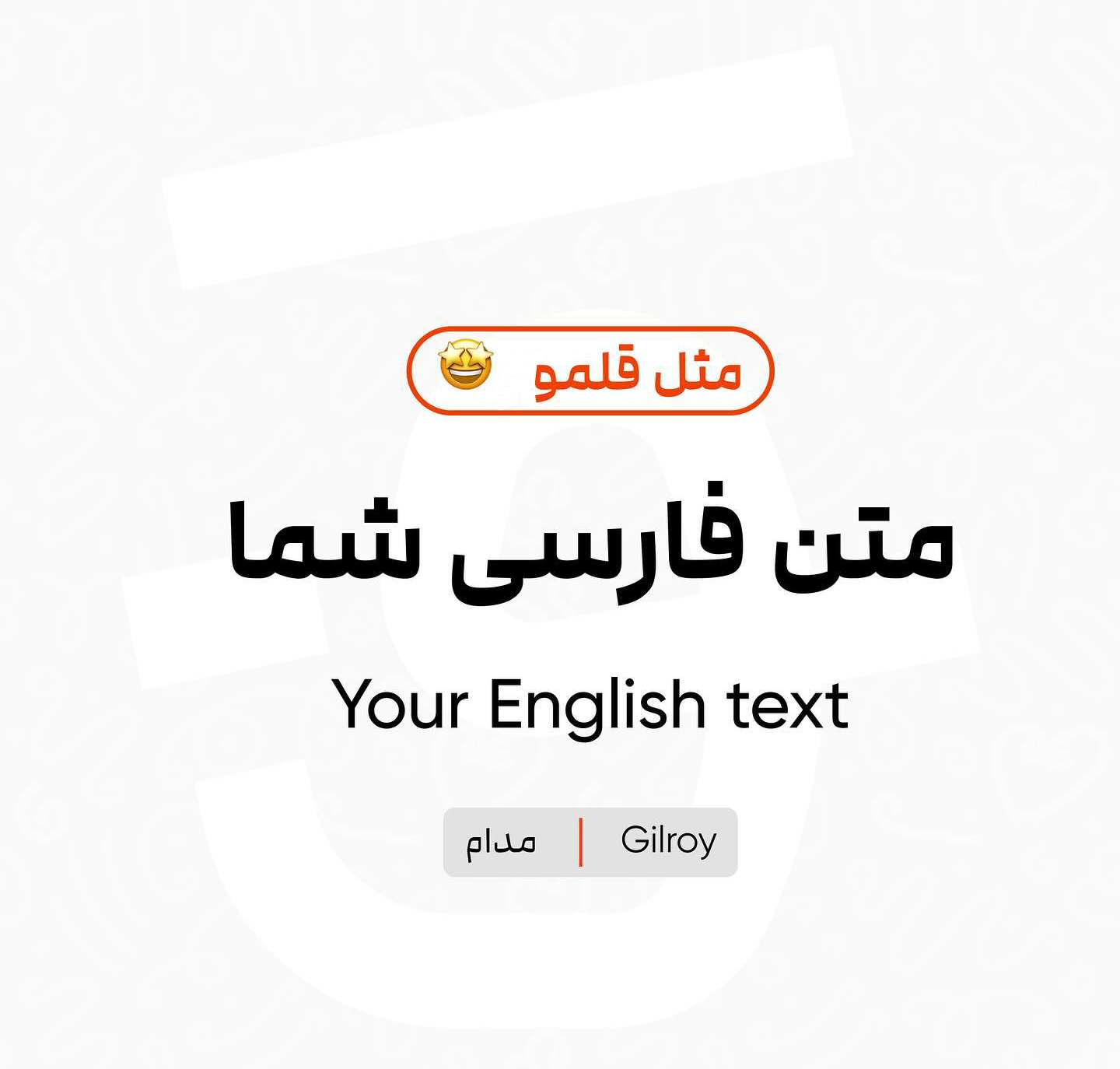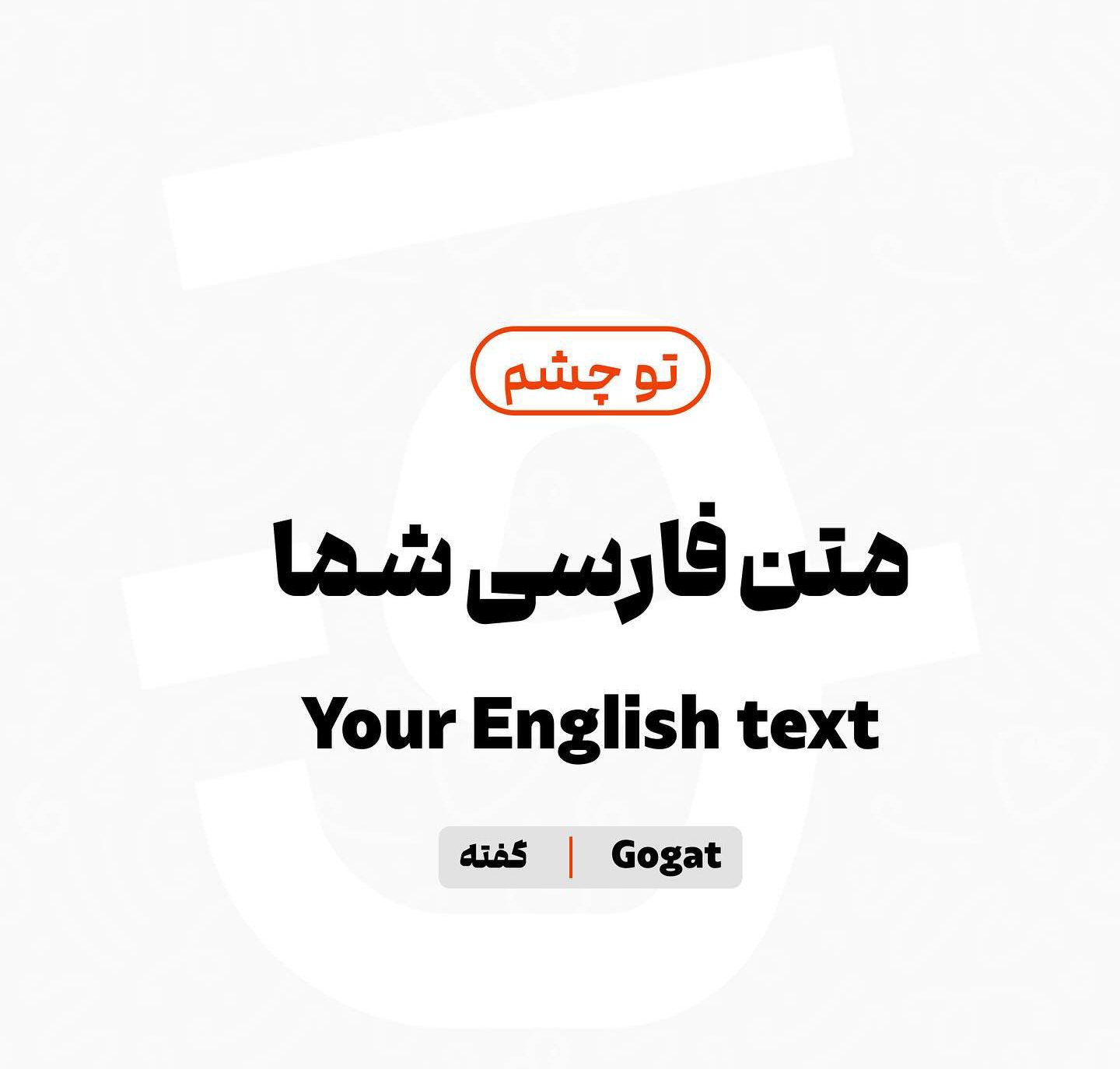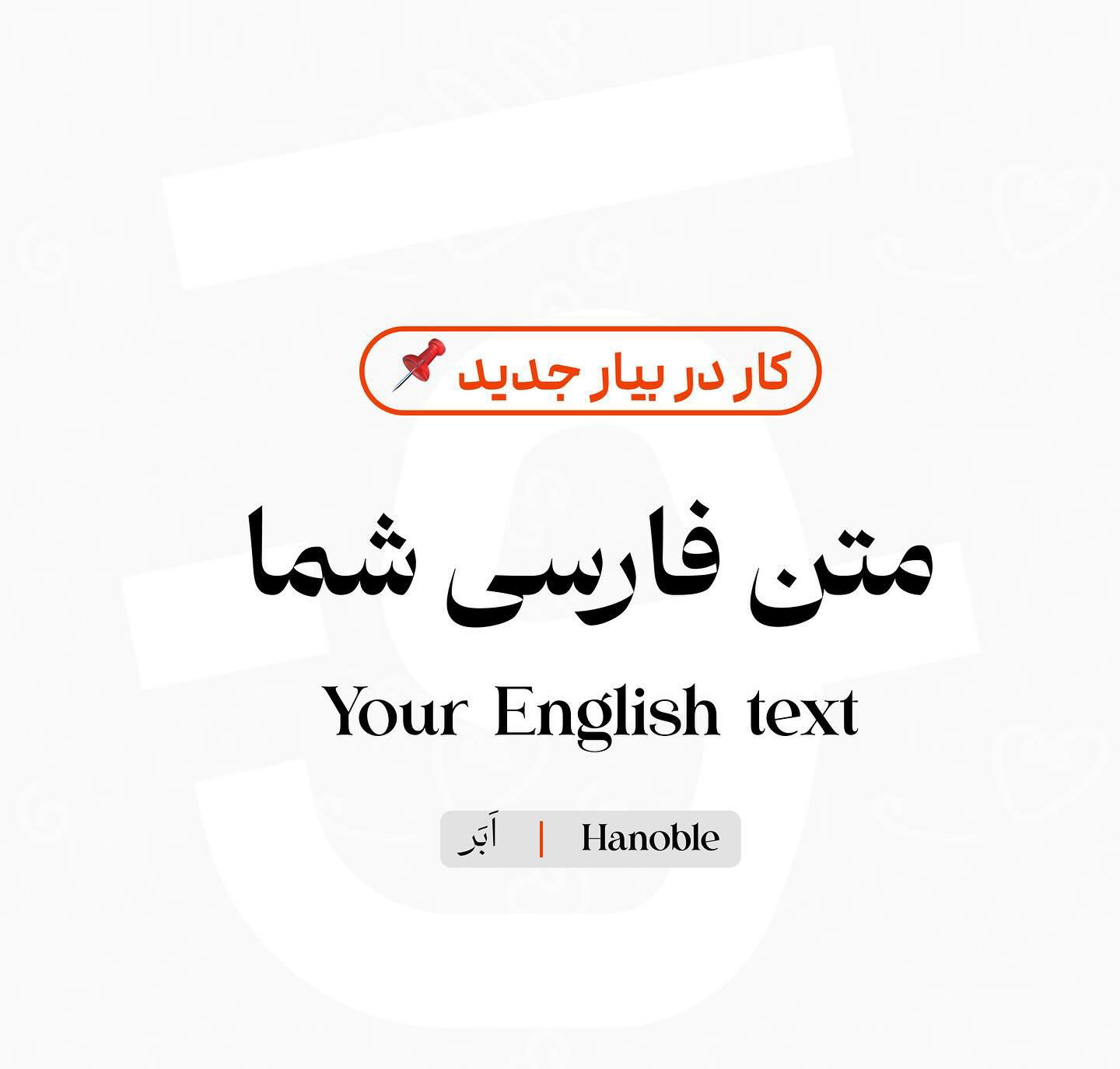
بهترین زوج فونت های فارسی و انگلیسی برای سایت
امروزه انتخاب فونت مناسب به یکی از اصول مهم طراحی سایت بدل شده است؛ چرا که مکملی بالقهوه برای شکلگیری و جانبخشی به صفحات وب است و به انطباق هرچه بهتر محتوا کمک میکند. در این میان انتخاب بهترین زوج فونت های فارسی و انگلیسی برای سایت هایی که ساختار چندزبانه دارند حائز اهمیت است.
ساختار حروف در دو زبان فارسی و انگلیسی با هم تفاوتهایی کلی دارد. به همین دلیل در طراحی فونت باید به شیوهای ضخامت، زوایای گردیها و چشمیها را در نظر گرفت که برای هر دو زبان مناسب باشد. در میان انبوه فونتهای فارسی امروز، طراحان به این نکته توجه ویژه دارند.
در ادامه این مقاله از سایت فونتچی، به بررسی چند فونت مختلف میپردازیم که ساختار طراحی حروف در آنها به شکل هماهنگ بوده و برای استفاده در سایت یا اپلیکیشن موبایل، میتواند ساختاری یکپارچه در اختیارتان قرار دهد. خصوصا برای سایتهای چند زبانه، که اهمیت خوانایی بین دو زبان بیشتر اهمیت پیدا میکند. علاوه بر آن به معرفی فونت انگلیسی مناسب برای هر یک خواهیم پرداخت که در صورت تمایل میتوانید از فونت جداگانه برای هر زبان استفاده کنید.
بهترین زوج فونت های فارسی و انگلیسی برای سایت
چند مسئله مهم در انتخاب فونت مناسب برای زبان انگلیسی و فارسی وجود دارد که عبارتند از:
- خوانایی حروف: فونت باید حروف را به طور واضح، خوانا و بهدور از اشکالات نمایش دهد. در هر دو زبان، حروف باید به خوبی تمایز داده شده و به اندازه کافی بزرگ و واضح باشند.
- تطابق شکل حروف: شکل حروف فارسی و انگلیسی در تمامی بخشها مثل زوایا، دندانهها، خطوط قائم و چشمیها با هم هماهنگ و یکپارچه باشد.
- رعایت فضای کافی بین حروف: حروف در زبان انگلیسی از هم جدا هستند؛ در حالی که زبان فارسی حروف به هم چسبیده کلمات را تشکیل میدهد. عدم رعایت فاصله حروف در زبان انگلیسی مشکلی است که گاها در برخی فونتها میبینیم.
- توازن بین کلاسیک و مدرن بودن: از آنجا که حروف کاملا متفاوت از هم بوده و کلمات از هم جداست، فونت باید توازن مناسبی بین ساختار کلاسیک و مدرن داشته باشد؛ به گونهای که با محتوای سایت هماهنگی داشته باشد.
- پشتیبانی از کاراکترهای خاص: فونت باید از تمامی کاراکترهای خاص و نشانههای زبانها پشتیبانی کند تا در نمایش متن مشکلی ایجاد نشود. خصوصا اینکه کاراکترها به دلیل ساختار راستچین و چپچین بودن دو زبان با هم متفاوت هستند.
حال با توجه به این نکات در ادامه به معرفی چند زوج فونت مناسب فارسی و انگلیسی، میپردازیم که با پشتیبانی از وزنهای چندگانه، حروف جایگزین و نسخه وریبل میتوانید از آنها در سایت خود بهترین استفاده را داشته باشید. پیش از این نیز در مقالهای به بررسی بهترین فونت برای سایت پرداختهایم که پیشنهاد میکنیم آن را نیز مطالعه کنید.
فونت ایران یکان ایکس با Raleway
فونت ایران یکان X اثری از مسلم ابراهیمی است که به عنوان یک فونت میانه از بین دو فونت یکان و ایران سنس طراحی شده است. این فونت تا بهامروز جزو محبوبترین فونتهای سایت بوده است که فروشگاههای اینترنتی و سایتهای بزرگی از آن استفاده میکنند.
شخصیت فونت ایران یکان با اینکه رسمی به نظر میرسد، اما در عینحال مدرن است و با توجه به سبکی که در طراحی آن پیادهسازی شده است، خوانایی بسیار خوبی را در تمامی وزنها دارد.
تنوع وزن بالا، پشتیبانی از نسخه وریبل، داشتن حروف و ترکیبات جایگزین متعدد، سبک نقطهگذاری چندگانه و پشتیبانی از زبانهای مختلف از ویژگیهای مهم این فونت به حساب میآید.
حروف انگلیسی در فونت ایران یکان همان سبک طراحی نسخه فارسی را دارند. فاصله حروف از یکدیگر استاندارد است که خوانایی لازم را چه در عناوین و چه در متنهای بلند به خوبی حفظ میکند.
ایران یکان نیز جزو فونتهای حرفهای است که چه در نسخههای فارسی و چه انگلیسی، به خوبی نیازتان را برطرف خواهد کرد. اما ترکیب آن با فونت انگلیسی Raleway میتواند ترکیبی از ظاهر رسمی اما مدرن فراهم آورد.
فونت پلاک با Ginto nord
پلاک دیگر زوج فونت مناسب انگلیسی و فارسی است که میتوانید در صفحات سایت و موبایل از آن استفاده کنید. این فونت هم طراحی نزدیک به فونتهای ایران یکان و ایران سنس را دارد. حروف به حدی نرم هستند که ساختار خودمانی داشته و در خواندن متون طولانی اصلا موجب خستگی چشم نخواهد شد.
اما در نسخه انگلیسی این فونت برای اینکه ساختار آن کمی نمایشیتر شود، حروف ارتفاع کمتری دارند به گونهای که احساس میکنید فشرده شده باشند و برای اینکه این فشردگی زیاد از حد خود را نشان ندهد، حروف با فاصله بیشتری از هم طراحی شدهاند.
استفاده از فونت پلاک به لطف همین نوع طراحی در وزنهای بالا و برای فونت عناوین میتواند انتخاب عالیتری باشد. چرا که خوانایی بهتری را ایجاد کرده و در جلب توجه نگاه مخاطب نیز موثرتر عمل میکند.
فونت پلاک هم خانوادهدار بوده و از ۸ وزن مختلف پشتیبانی میکند. به منظور نمایشیتر کردن این فونت در عناوین، وزنهای خیلی ضخیم و سیاه دارای سبک نقطهگذاری پیوسته هستند که انتظار میرود در آپدیتهای بعدی این فونت نسخه وریبل نیز به آن افزوده شود.
فونت پلاک هم با اینکه خود دارای نسخه انگلیسی به همان سبک فارسی است، اما اگر به هر دلیل تمایل به استفاده فونتی کاملا جدا برای زبان انگلیسی هستید، میتوانید قلم Ginto nord را با آن ترکیب کنید تا ضمن ارائه شخصیتی خودمانی به متون فارسی، شخصیت کلی فونت ساختاری باحال داشته باشد.
جمعبندی نهایی
با توجه به نکاتی که در این مقاله برای انتخاب بهترین زوج فونت فارسی و انگلیسی برای سایت ذکر کردیم، توجه به تفاوتهای شکلی حروف در زبانها موضوعی حائز اهمیت است. فونت انتخابی باید هماهنگی بین زیبایی و خوانایی را فراهم کند؛ بهطوری که در خوانایی متون بلند و طولانی موجب خستگی چشم نشده یا اینطور هم نباشد که وجود کلمات لاتین به دلیل ساختار متفاوت زبانی، باعث برهم زدن تمرکز خواننده روی متن شود.